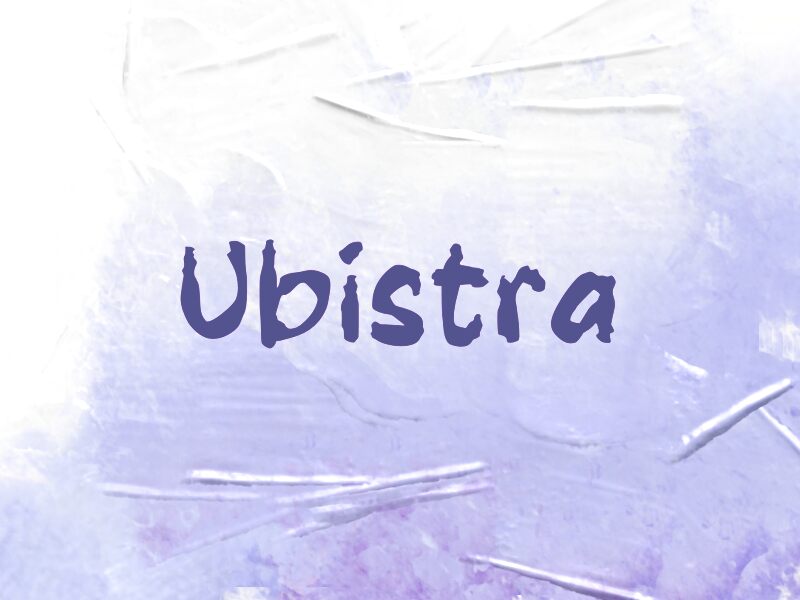
Ubistra
Ubistra, realizzata da Wep, è un font gratuito in stile «dry-brush» che conserva tutto il fascino grezzo della pittura a mano. Le lettere sembrano tracciate con un pennello carico di colore: estremità smussate, bordi irregolari e curve dense e cariche d'inchiostro donano al design un'energia immediata, tipica dei poster, che rompe con la monotonia di una normale scrittura corsiva.
È perfetta per flyer musicali, grafiche streetwear, copertine indie, scritte su lavagna per caffè e titoli brevi di packaging, dove quella consistenza ruvida può esprimersi al meglio. Come font gratuito, Ubistra dà il suo meglio in applicazioni display come titoli, intestazioni d'impatto per i social e parole chiave in grande formato, dove i suoi tratti di pennello decisi rendono il messaggio diretto e autentico.